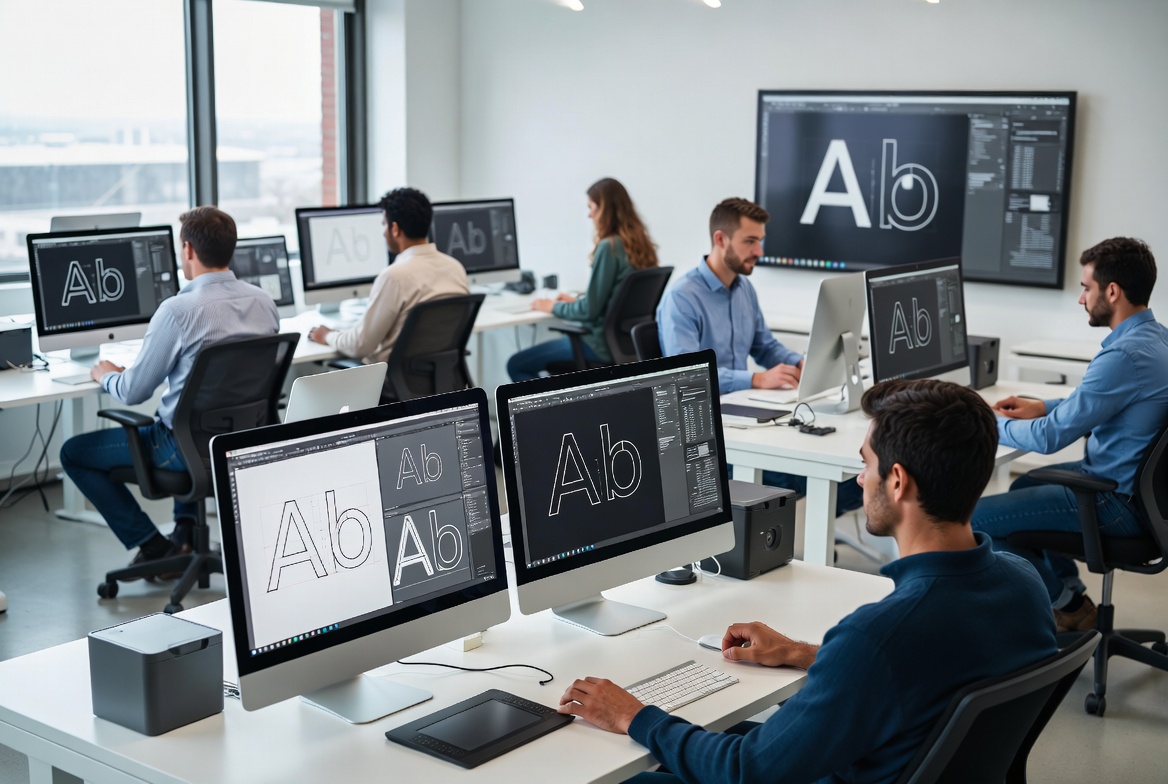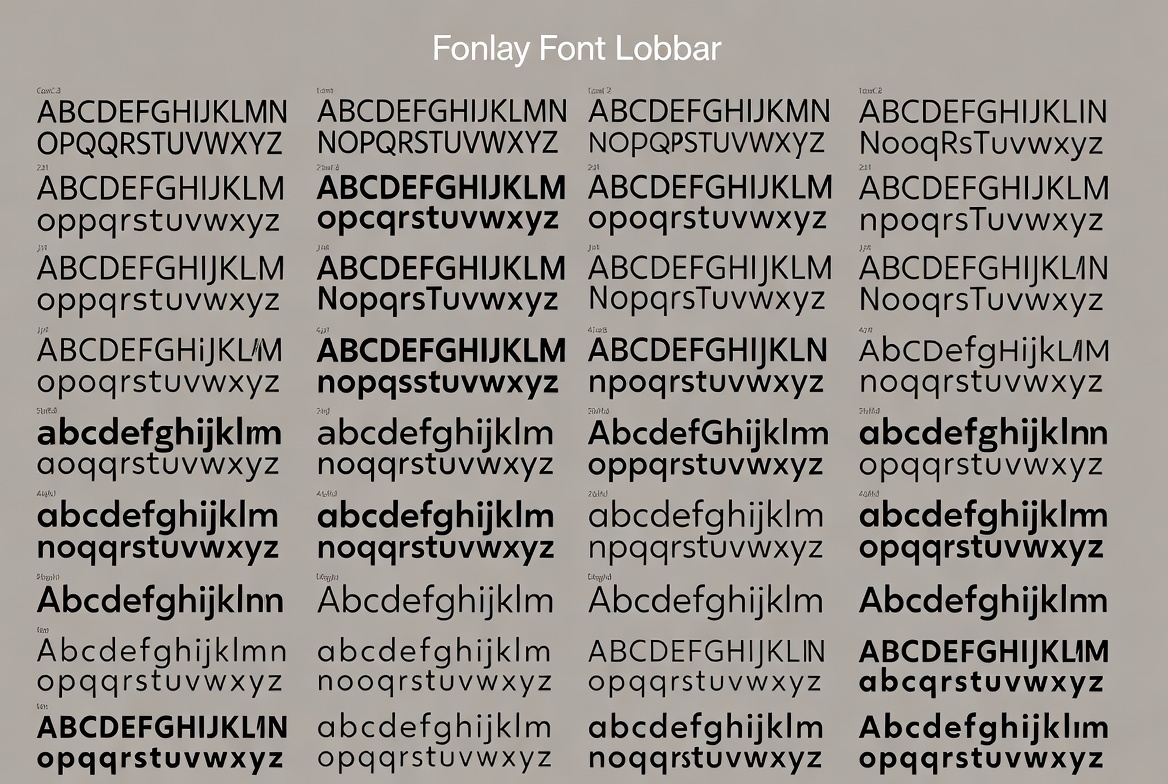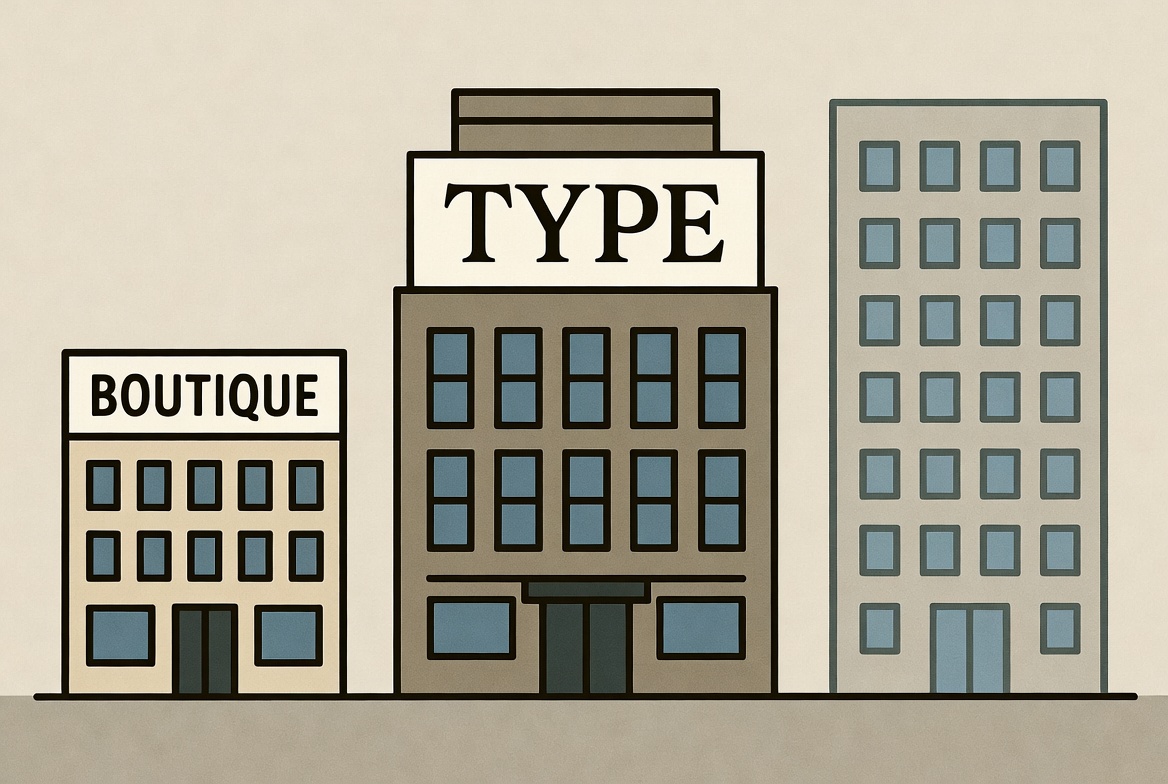
Schriftenhersteller – Teil 4: Größere unabhängige Foundries
Zwischen Boutique-Studio und Konzern: Größere unabhängige Foundries wie TypeType und ihre Rolle im heutigen Schriftmarkt.
In den vorherigen Teilen dieser Serie haben wir die großen Player (Monotype, Adobe Fonts, Google Fonts) und die klassischen designorientierten Independent-Foundries betrachtet. Dazwischen gibt es eine weitere Gruppe: größere unabhängige Foundries.
Diese Studios sind deutlich größer und produktiver als die klassischen Boutique-Foundries, gehören aber nicht zu den Konzernen. Sie verbinden Unabhängigkeit mit einer klar kommerziellen und internationalen Ausrichtung.
Was größere unabhängige Foundries auszeichnet
Illustration: Größere unabhängige Foundries arbeiten oft mit mehreren Designern und einer professionellen Infrastruktur
Im Vergleich zu kleinen designorientierten Studios weisen sie typischerweise folgende Merkmale auf:
- Deutlich größere Teams (oft mehrere Dutzend Mitarbeiter)
- Umfangreiche Schriftbibliotheken mit vielen Familien und Schnitten
- Starke Präsenz auf internationalen Marktplätzen
- Fokus auf vielseitig einsetzbare, feature-reiche Schriften
- Professionelle Infrastruktur für Lizenzierung, Customization und Support
Gleichzeitig bleiben sie rechtlich und organisatorisch unabhängig von den großen Konzernen.
TypeType als Beispiel
Ein markantes Beispiel für diese Kategorie ist TypeType.
Die Foundry wurde 2013 gegründet und hat sich von einem kleinen Studio zu einem international tätigen Unternehmen mit einem größeren Team entwickelt. TypeType ist besonders bekannt für umfangreiche, gut ausgebaute Schriftfamilien, die sowohl lateinische als auch kyrillische Zeichensätze abdecken.
Zu den bekanntesten Veröffentlichungen gehören unter anderem TT Norms und TT Commons. Viele ihrer Schriften sind auf eine breite Einsetzbarkeit in Branding, UI und Editorial Design ausgelegt und werden von Unternehmen weltweit genutzt.
TypeType steht damit prototypisch für eine Foundry, die:
- unabhängig geblieben ist,
- gleichzeitig eine hohe Produktivität und Marktreichweite erreicht hat,
- und sich klar von den klassischen kleinen Design-Studios unterscheidet.
Weitere Vertreter dieses Typs
Illustration: Umfangreiche Schriftbibliotheken mit vielen Familien und Schnitten
Neben TypeType gibt es weitere Foundries, die in eine ähnliche Kategorie fallen. Sie operieren mit größeren Teams, pflegen umfangreiche Kataloge und bedienen einen internationalen Markt, ohne Teil von Monotype oder vergleichbaren Konzernen zu sein.
Gemeinsam ist diesen Anbietern, dass sie eine Art Mittelbau im Schriftmarkt bilden: größer und marktorientierter als Boutique-Studios, aber nicht so dominant und konsolidiert wie die großen Plattformen.
Bedeutung für Anwender
Für Designer und Unternehmen können größere unabhängige Foundries eine interessante Option sein:
- Sie bieten oft ein gutes Verhältnis von Qualität, Umfang und Preis.
- Viele Schriften sind technisch sehr vollständig (große Zeichensätze, Variable Fonts, gute Sprachunterstützung).
- Die Unabhängigkeit vom Konzernumfeld kann bei Lizenzfragen und direkter Kommunikation Vorteile haben.
Gleichzeitig unterscheiden sie sich in der gestalterischen Haltung häufig von den stark autorenbezogenen Boutique-Foundries. Die Schriften sind oft eher auf breite Nutzbarkeit als auf starke gestalterische Eigenwilligkeit ausgelegt.
Illustration: Größere unabhängige Foundries stehen zwischen klassischen Boutique-Studios und großen Konzernen